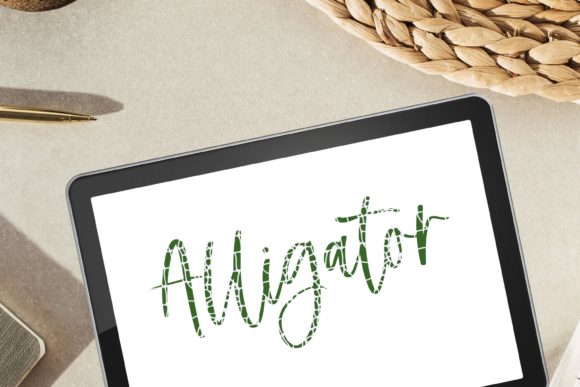
Alligator Procreate Lettering Brush
Если вы ищете высококачественные ресурсы, такие как Alligator Procreate Lettering Brush, этот премиум-пакет — фантастический выбор для ваших творческих проектов.
Создаете ли вы продукты POD (печать по требованию), свадебные приглашения или графику для социальных сетей, Alligator Procreate Lettering Brush станет идеальным выбором.